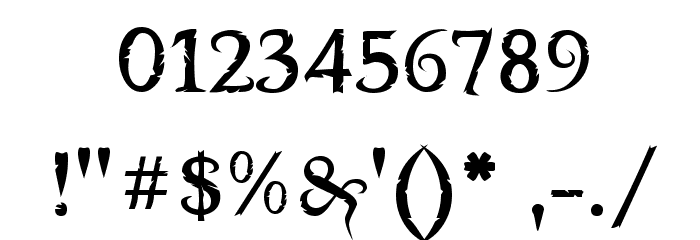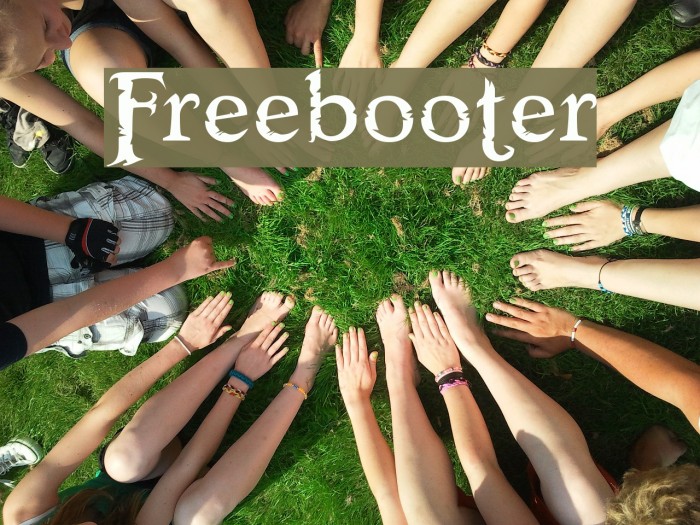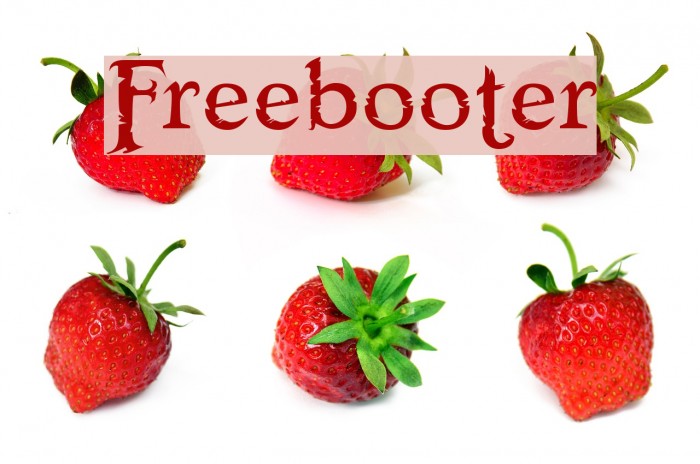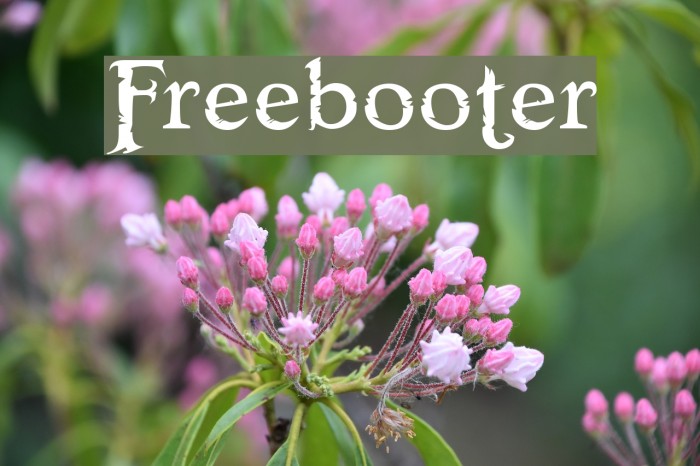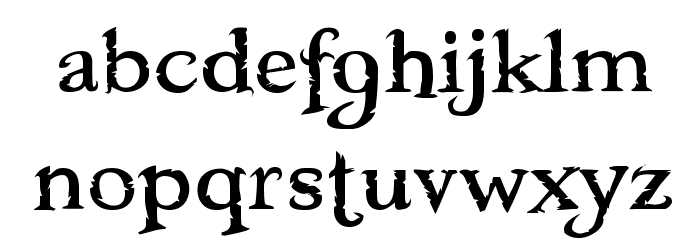
Freebooter Font
✎ Serif
Fonts by Graham Meade - GemFonts
| Рекомендуемые проекты | Ideal for themed event invitations, pirate-themed games, historical posters, and adventure book covers. |